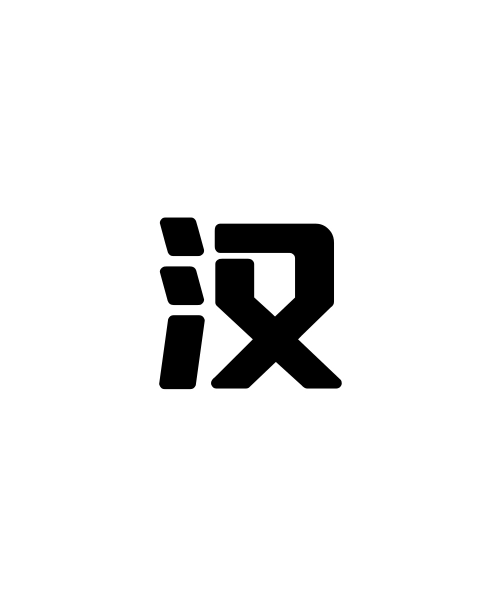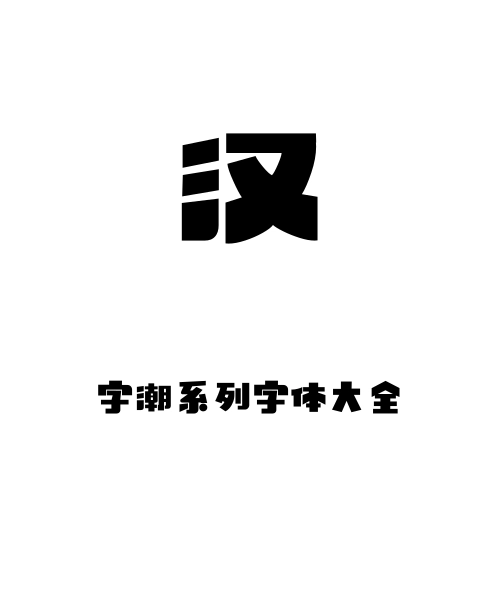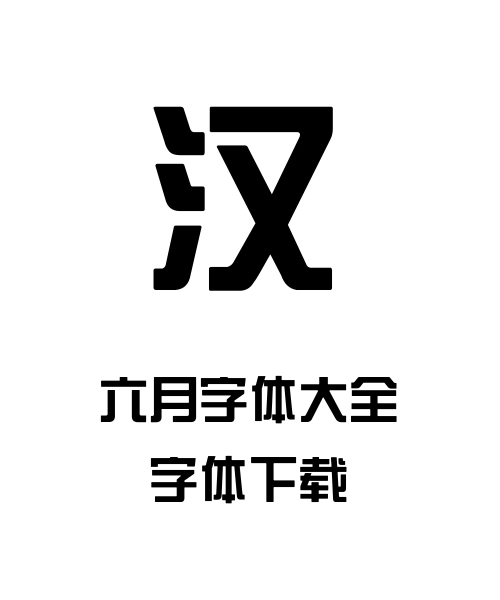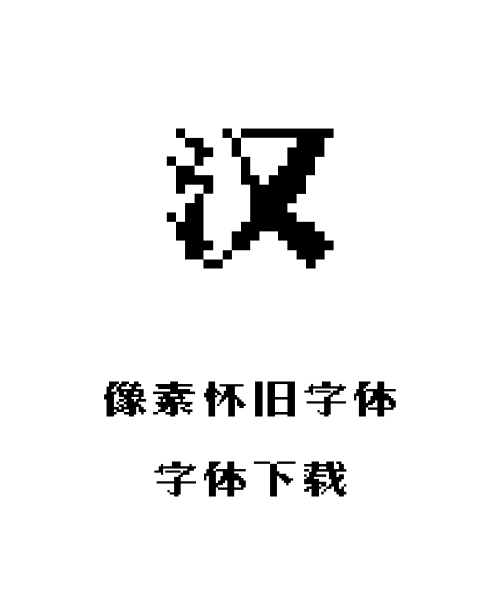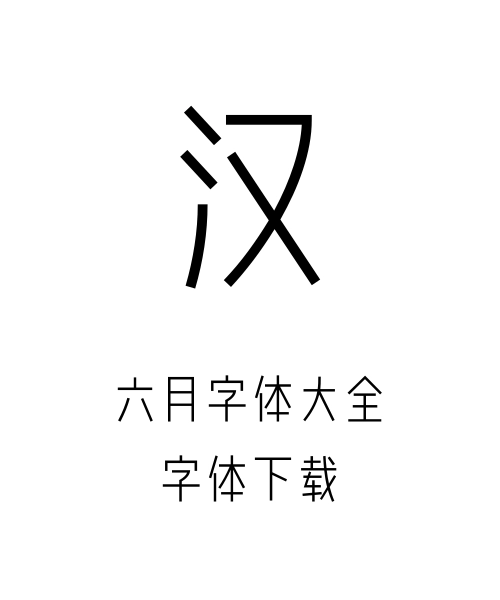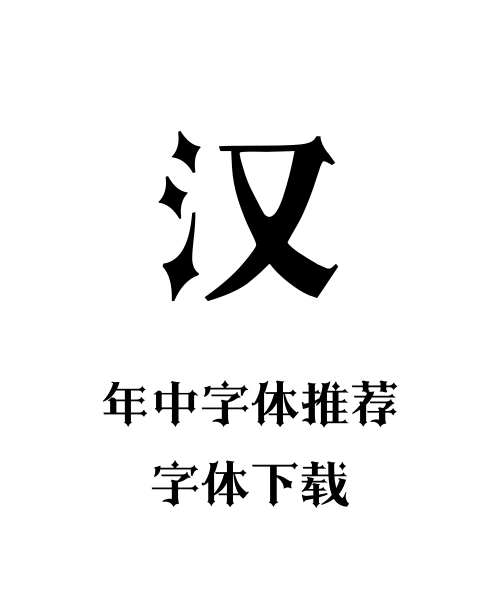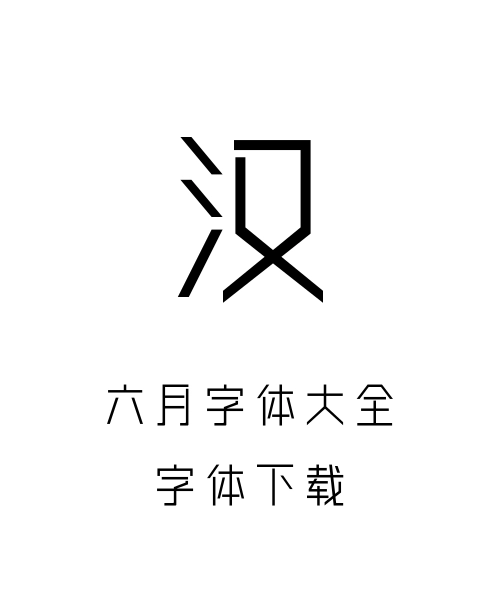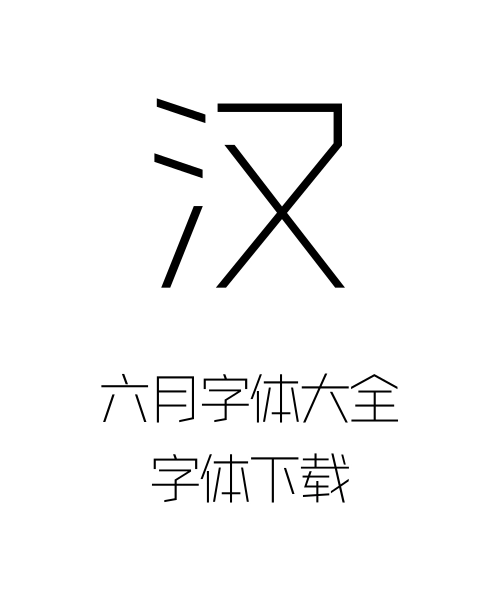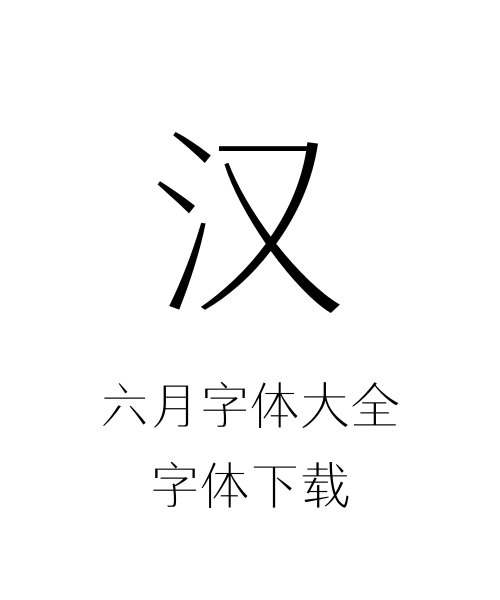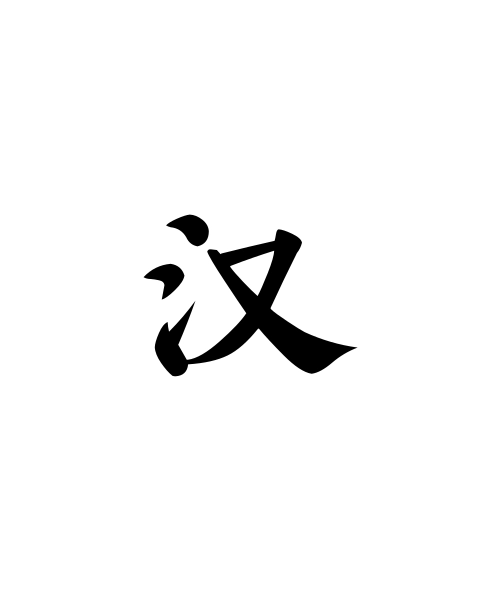
#健身房器械标识字体合集 共6款
笔画硬朗方角,加粗至字重750,结构紧凑,适配器械使用说明、安全警示,清晰指引操作。
#儿童科普读物字体合集 共6款
笔画短粗圆角,结构饱满,字重450,适配科普绘本内页、少儿百科,亲和力强且易认。
#企业年报封面字体合集 共6款
笔画粗细分明,结构严谨无装饰,字重700,适配年报封面标题、财务摘要,强化专业信赖感。
#婚礼请柬标题字体合集 共6款
笔画圆润饱满,结构扁宽,字重600,适配请柬主标题、婚宴桌卡,传递温馨浪漫感。
#公共交通信息字体合集 共6款
笔画等粗平直,字距宽松,结构瘦长,适配公交站牌、地铁线路图,快速扫读不串行。
#博物馆展品说明字体合集 共6款
笔画中等粗细,转折微圆角,字形端正,适配文物介绍牌、展柜标签,庄重且亲和。